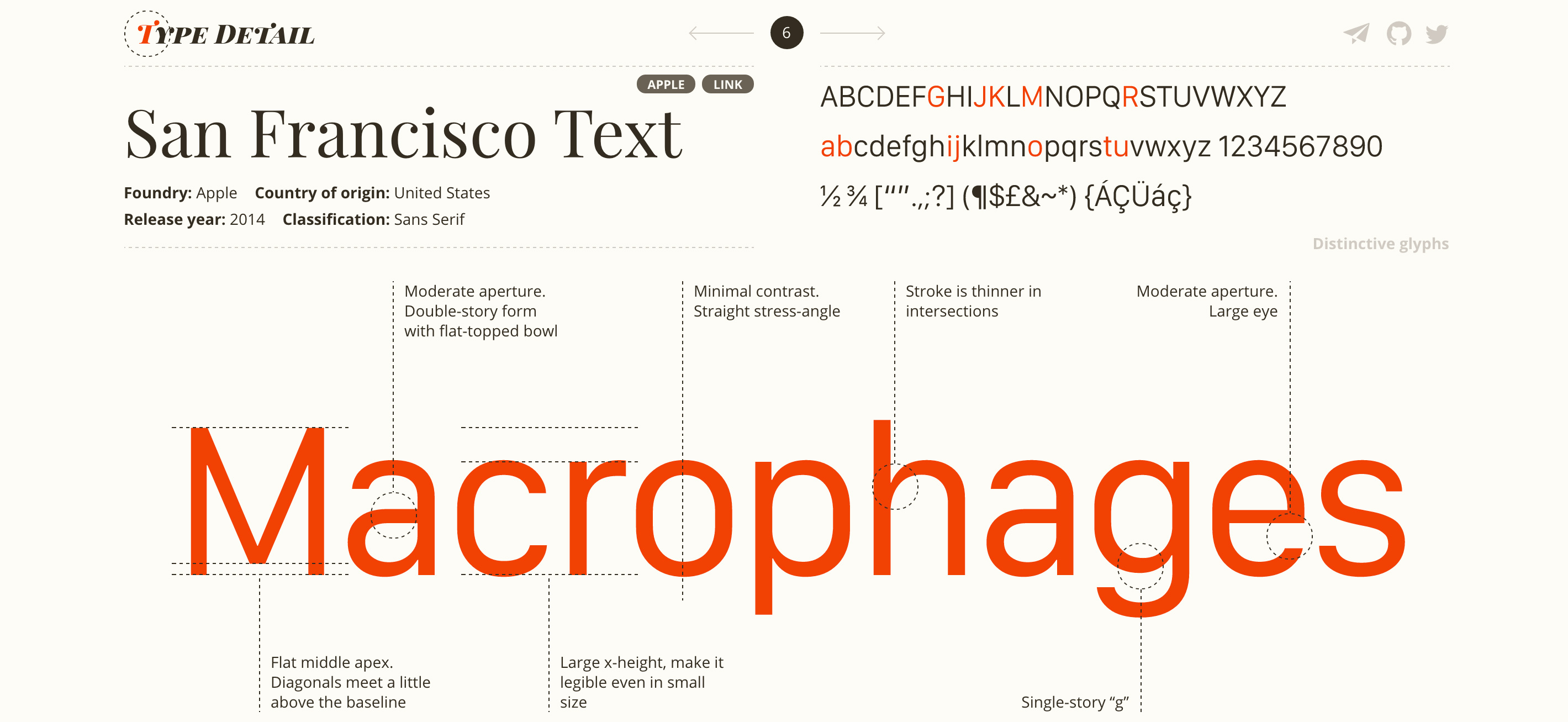
Type Detail è un progetto della designer Wenting Zhang. Ha due fonti di ispirazione, il libro di Stephen Coles The Anatomy of Type e l’iniziativa 100 day project del magazine The Great Discontent, e un obiettivo personale: migliorare la propria tipografia.
Wenting Zhang in un’intervista su Medium per TypeThursday racconta di come da studente alle prese con suoi primi lavori si è sentita ripetere spesso che la sua tipografia non era buona.
[quote] When I showed my work, constantly people pointed out that the typography was not so great.[/quote]
Lavorando su Type Detail Zhang ha capito che le competenze tipografiche si sviluppano in tre fasi:
Fase 1: Over-Dramatic
La fase in cui i designer alle prime armi tendono a scegliere e usare caratteri che “spiccano” e che “gridano”. È la fase in cui spesso si scelgono font da siti tipo dafont.com e si tende ad usare troppo spesso font come Lobster. In questa fase l’occhio non è abituato a vedere le differenze dettagliate tra i font, ma solo le differenze più marcate. È anche la fase in cui capita di confondersi tra Arial ed Helvetica.
Fase 2: Classic
La fase in cui si tende ad andare sul sicuro seguendo in modo molto rigido le regole tipografiche fondamentali e usando solo caratteri classici, Gill Sans, Helvetica, Univers, Garamond, Futura, Bodoni, Baskerville. È una fase sicuramente più professionale e può durare anche molti anni. Zhang racconta di come in questa fase per non sbagliare nelle combinazioni di serif e sans-serif cerca di usare sempre caratteri della stessa type foundry.
Fase 3: Master
La terza, quella a cui aspira Zhang, è la fase in cui si riesce a fare scelte e considerazioni sui caratteri molto più consapevoli e ragionate, come combinare caratteri realizzati nello stesso periodo storico o che hanno caratteristiche simili.
Per entrare in questa terza fase la Zhang con Type Detail analizza font specificando e annotando le caratteristiche delle lettere: occhielli, legature, ascendenti, discendenti.